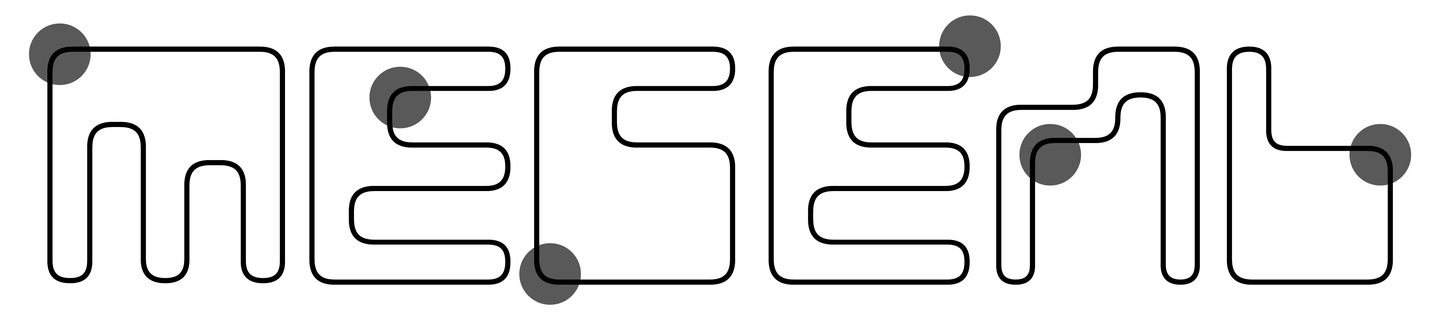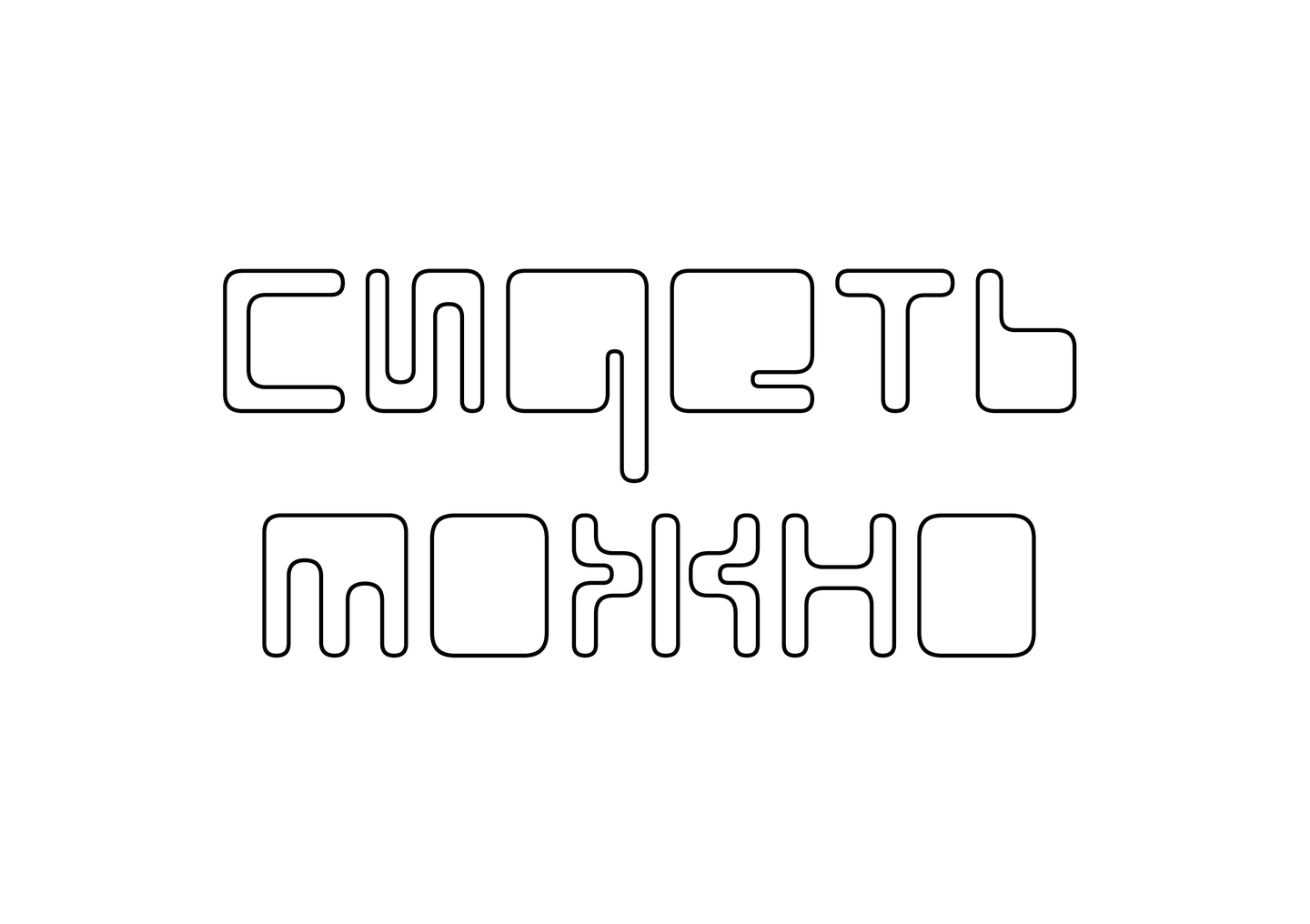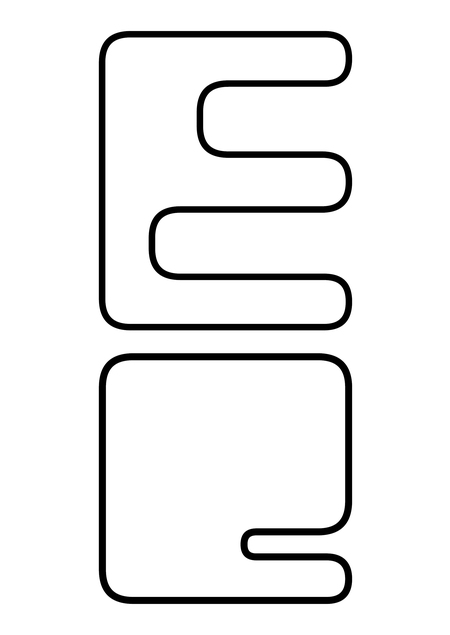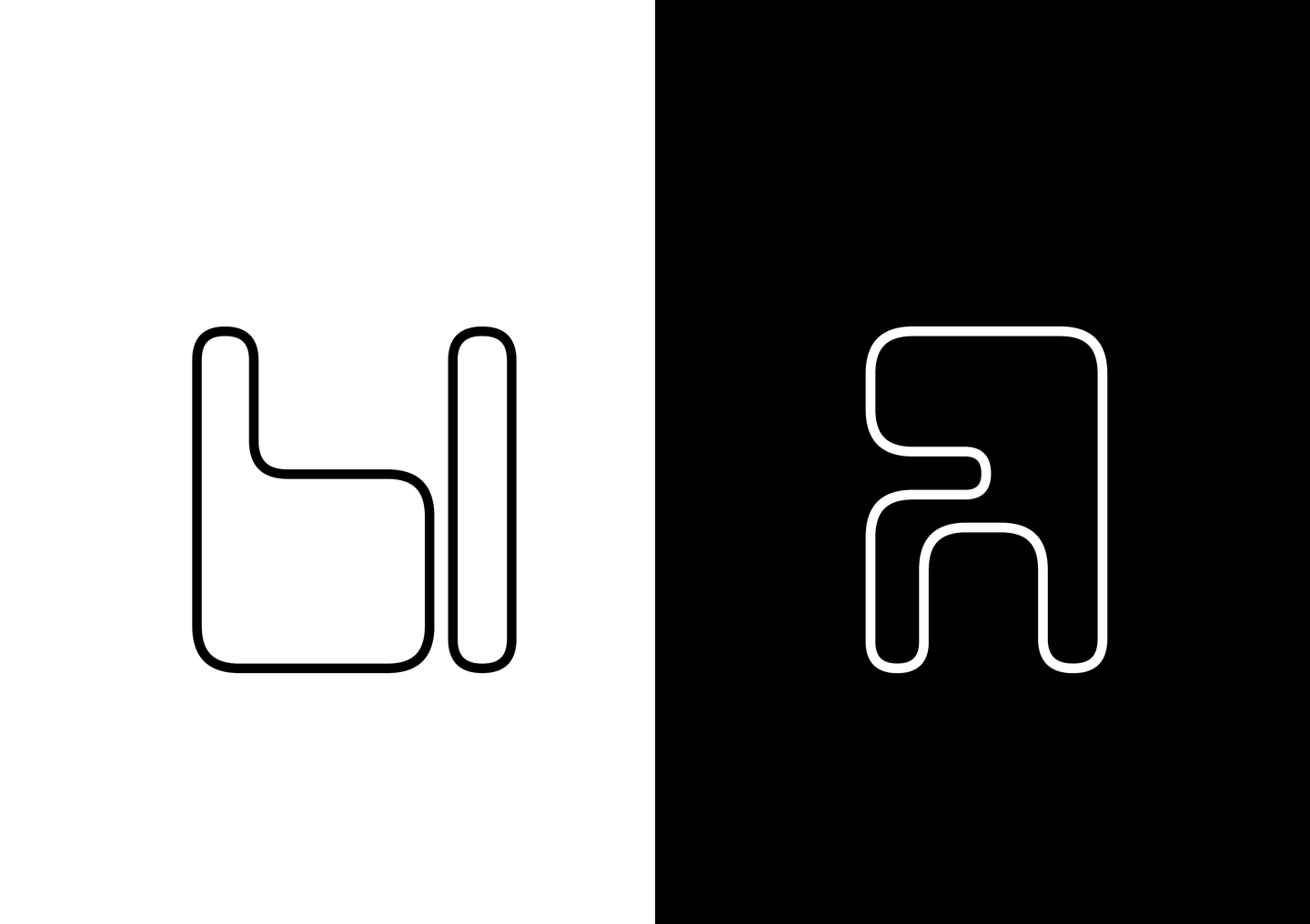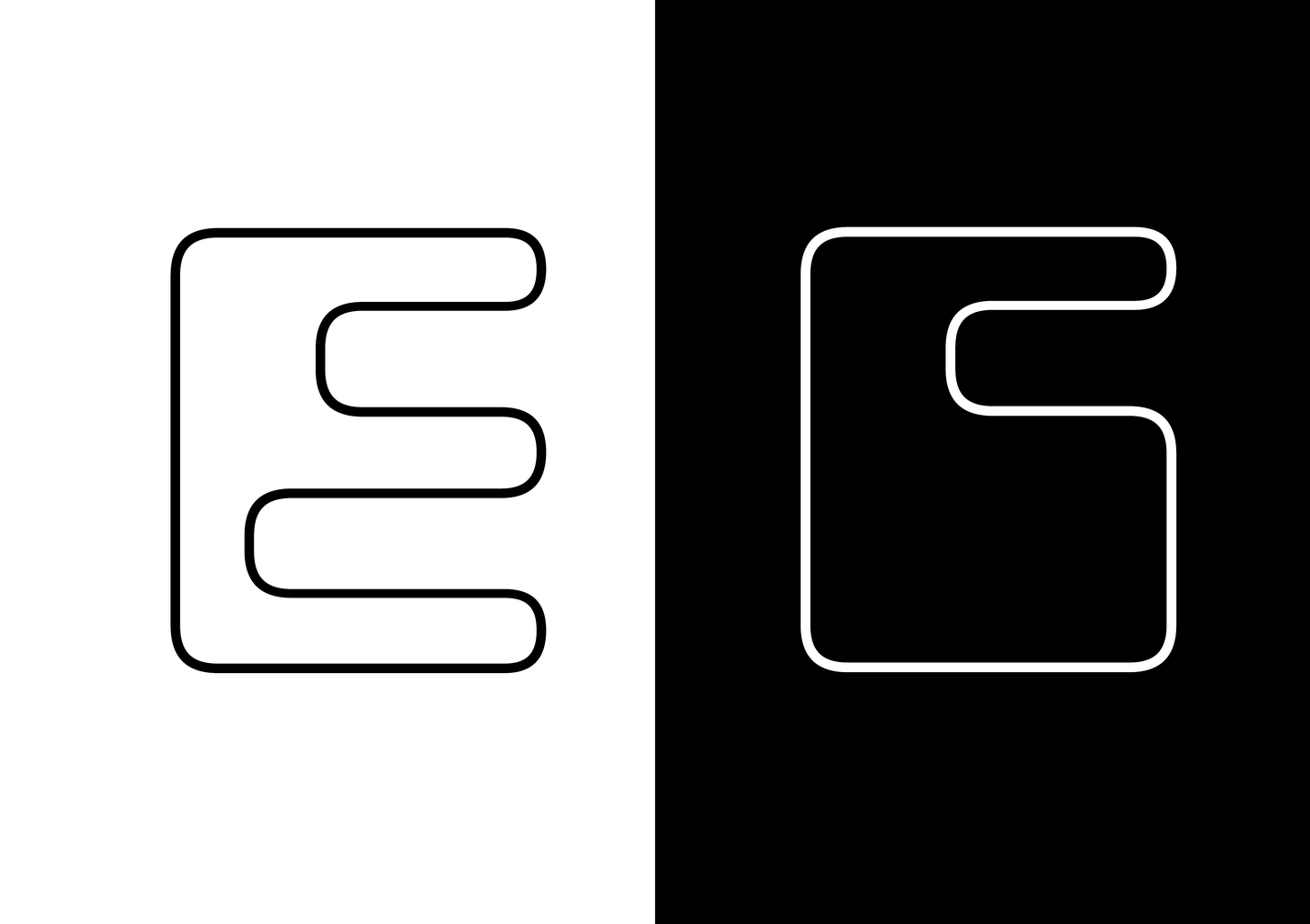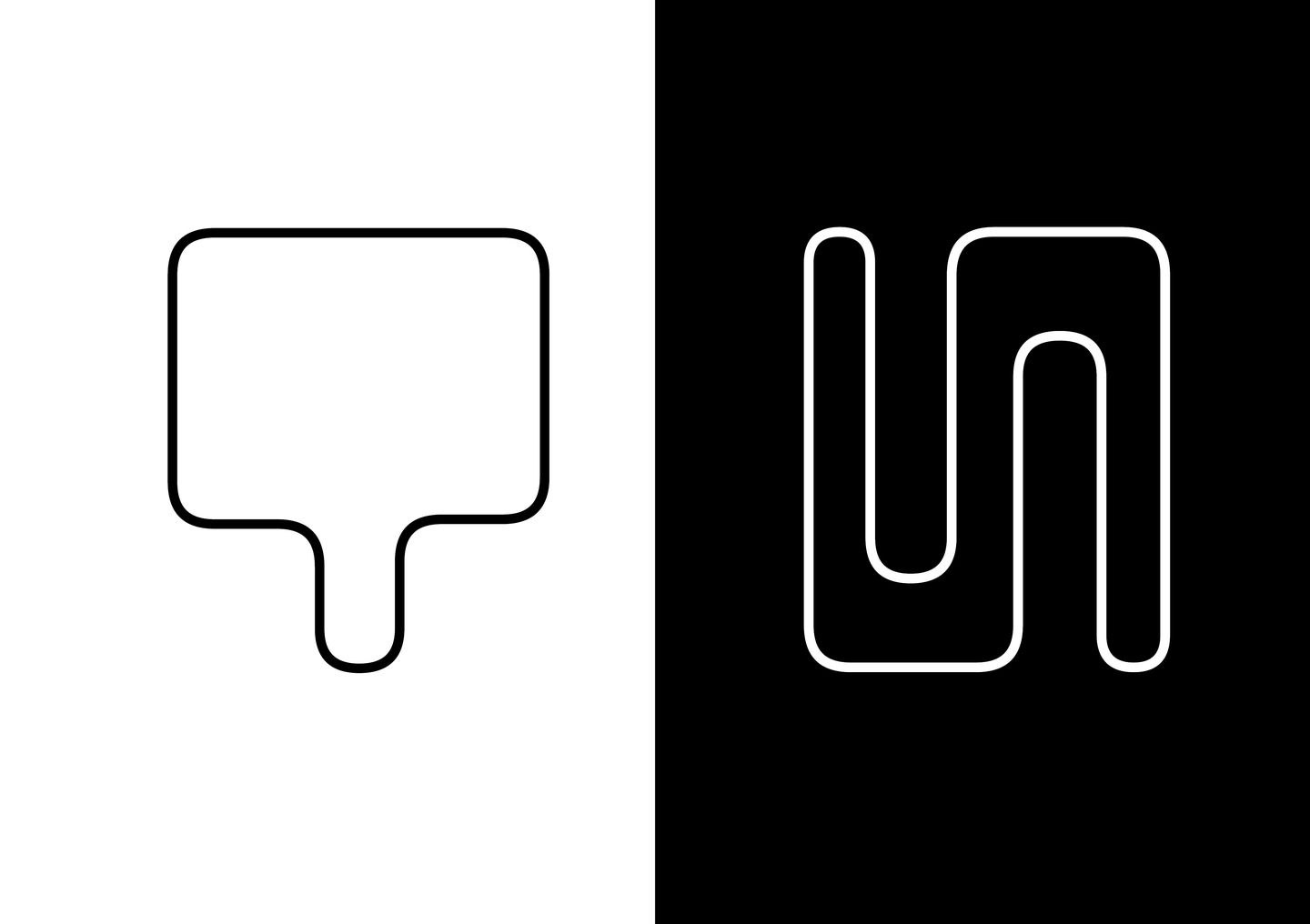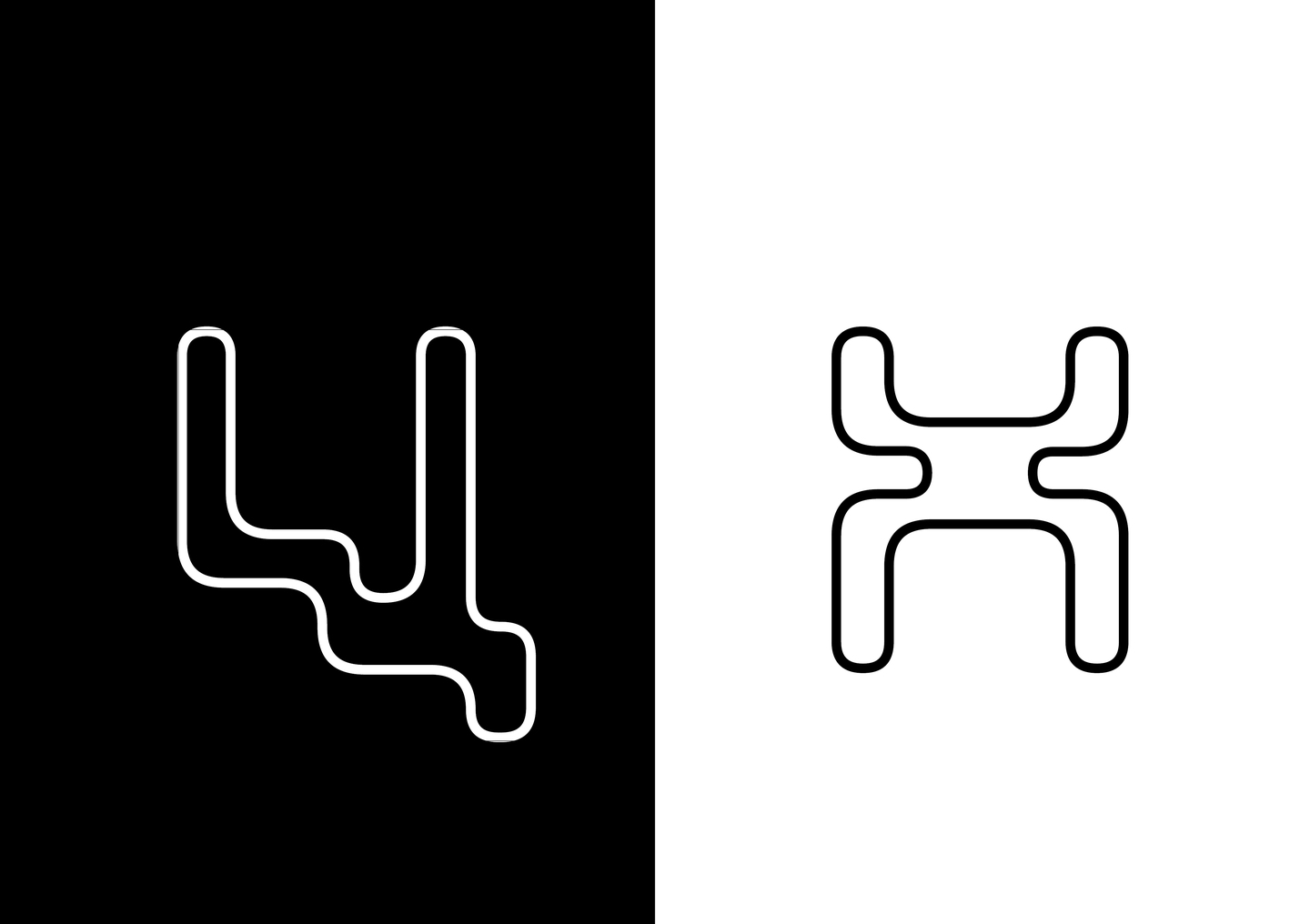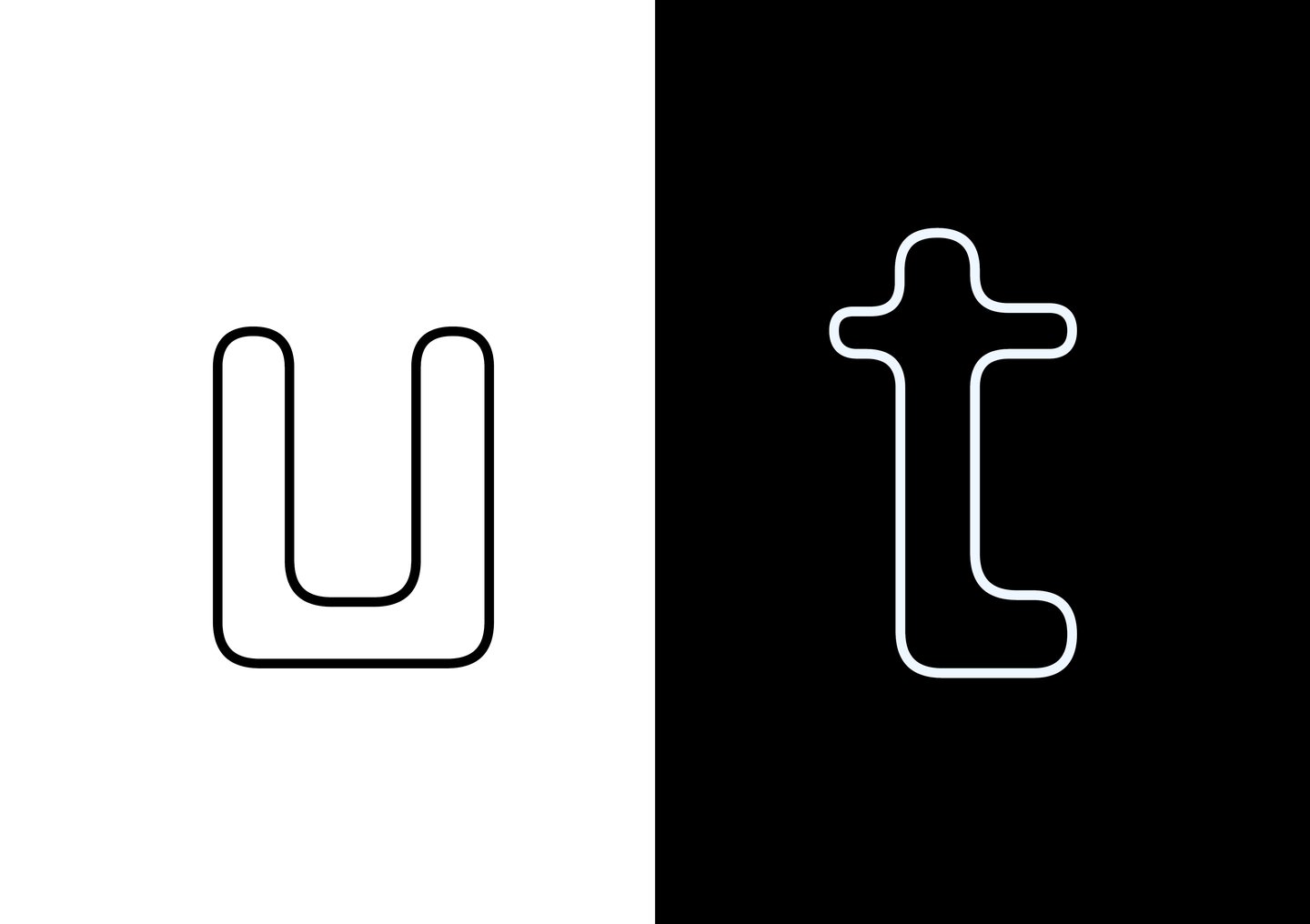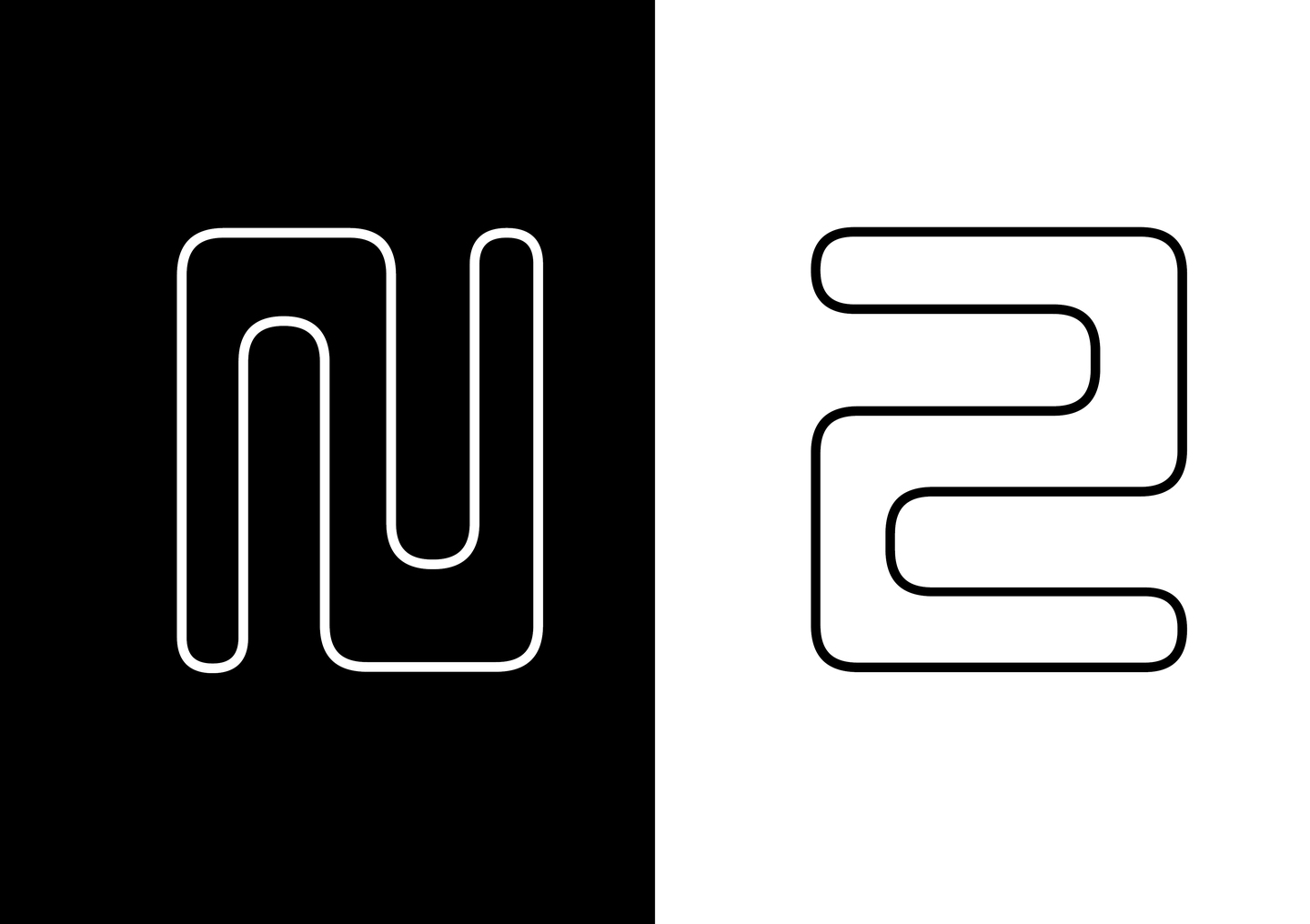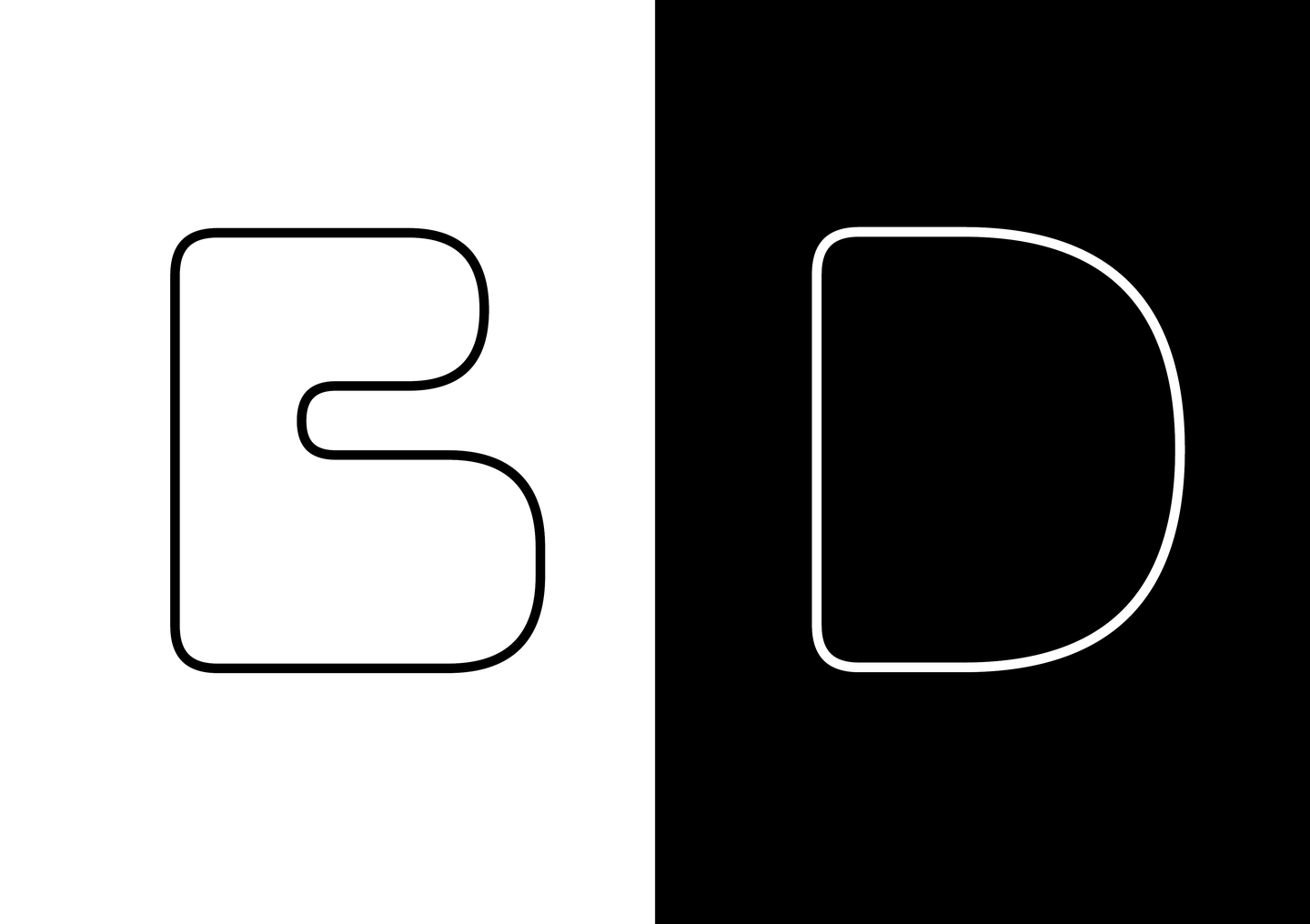
eburet font — это акцидентный шрифт. Основой для него послужила форма предметов, создаваемых одноименным брендом. В шрифте сочетаются ломанные диагонали с плавными линиями, которые повторяют силуэты объектов